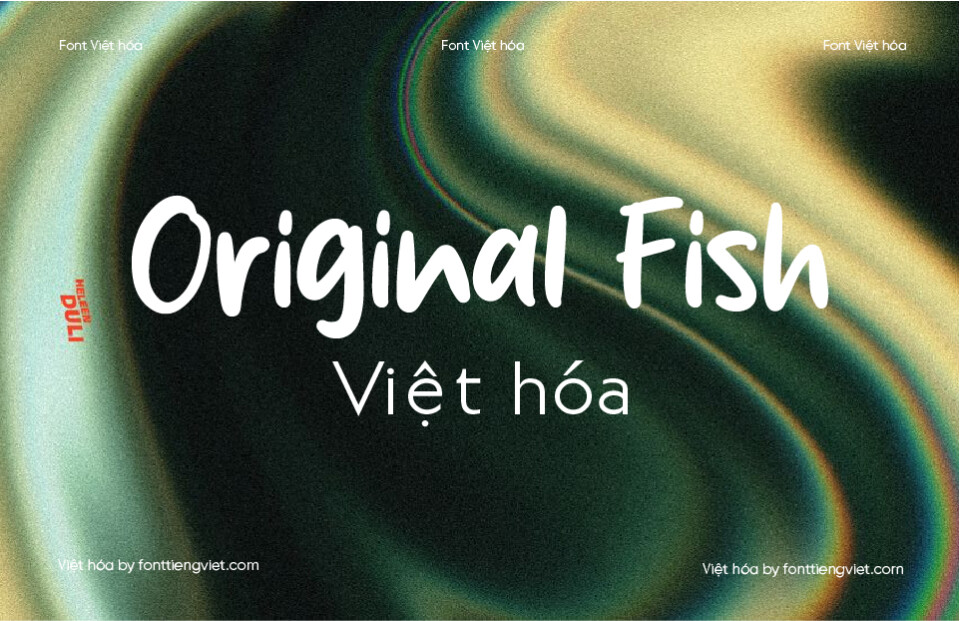
Font Việt hóa 1FTV VIP Original Fish – Sự lựa chọn hoàn hảo cho thiết kế sáng tạo
Khám phá sức hút của Font Việt hóa 1FTV VIP Original Fish
Trong thế giới đồ họa hiện đại, việc tìm kiếm một bộ Font Chữ độc đáo và ấn tượng luôn là ưu tiên hàng đầu của các nhà thiết kế. Font Việt hóa 1FTV VIP Original Fish nổi lên như một hiện tượng nhờ phong cách viết tay phóng khoáng, mang đậm hơi thở nghệ thuật đường phố và sự tự do. Đây là bộ phông chữ được tinh chỉnh kỹ lưỡng về dấu tiếng Việt, giúp người dùng dễ dàng ứng dụng vào các sản phẩm truyền thông mà không lo lỗi hiển thị. Với các đường nét uốn lượn mềm mại nhưng vẫn giữ được sự mạnh mẽ, bộ font này cực kỳ phù hợp cho các dự án thiết kế logo, bao bì sản phẩm hoặc các ấn phẩm quảng cáo dành cho giới trẻ.
Tại sao nên chọn Font Việt hóa 1FTV VIP Original Fish?
Điểm đặc biệt của Font Việt hóa 1FTV VIP Original Fish nằm ở cấu trúc chữ cái không đối xứng, tạo nên cảm giác tự nhiên như nét vẽ cọ thủ công. Điều này giúp các tác phẩm thiết kế trở nên có hồn và gần gũi hơn với người xem. Ngoài ra, bộ font còn hỗ trợ đầy đủ các ký tự đặc biệt, giúp bạn linh hoạt trong việc sáng tạo tiêu đề hay các đoạn văn bản ngắn cần sự phá cách.
Cách ứng dụng Font Việt hóa 1FTV VIP Original Fish trong học tập và công việc
Đối với học sinh và giáo viên, việc sử dụng các font chữ mới lạ như 1FTV VIP Original Fish sẽ giúp các bài thuyết trình hay báo cáo trở nên sinh động, thu hút sự chú ý của người nghe. Bạn có thể sử dụng font này để làm nổi bật các đề mục chính hoặc trang trí bìa tiểu luận. Trong công việc chuyên môn, bộ font là công cụ đắc lực để thiết kế áo thun, poster sự kiện hoặc các nội dung truyền thông trên mạng xã hội.
Lưu ý khi sử dụng font chữ
- Sử dụng font cho các tiêu đề lớn để tối ưu khả năng nhận diện.
- Kết hợp với các phông chữ không chân (Sans-serif) để tạo sự cân bằng cho bố cục.
- Kiểm tra kỹ khoảng cách chữ (kerning) khi thiết kế các cụm từ quan trọng.